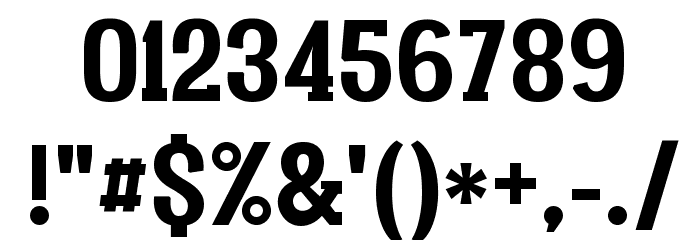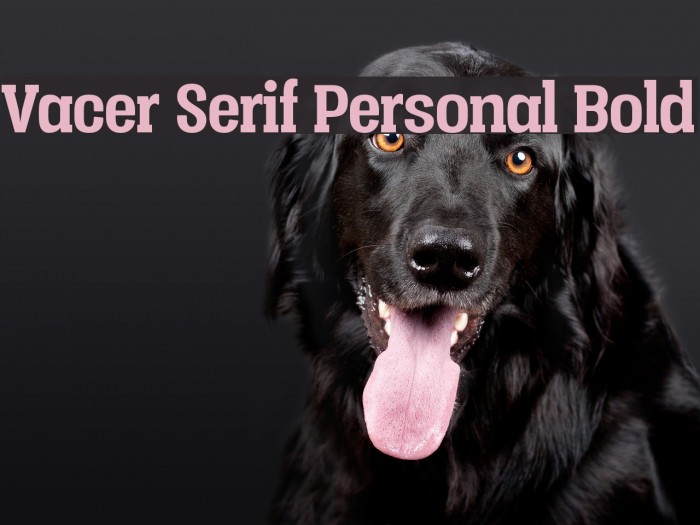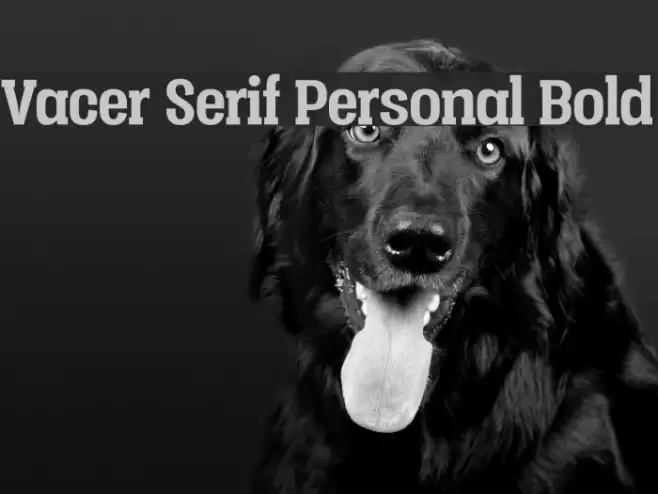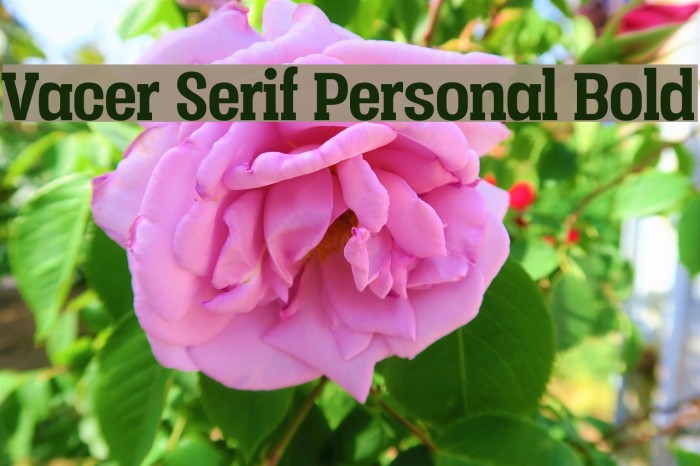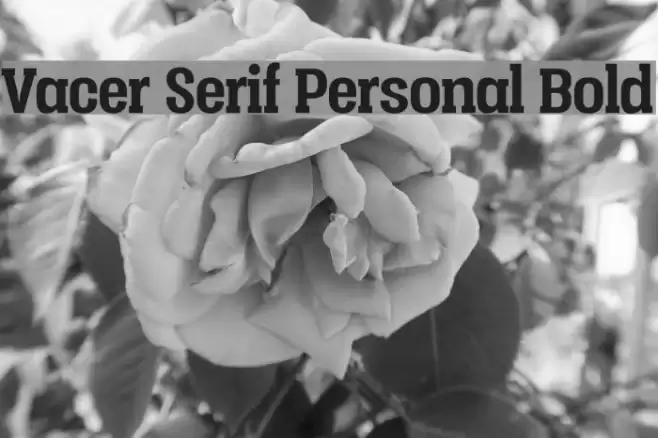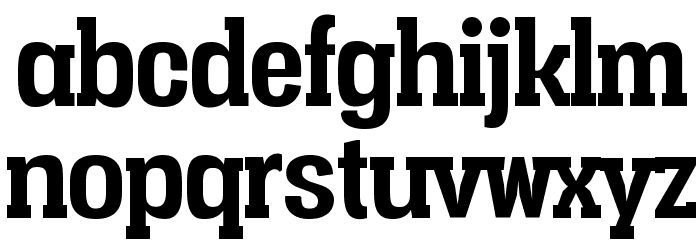
Vacer Serif Personal Bold Font
| Caz de utilizare | Headlines, Logos, Editorial Design |
| Proiecte propuse | Ideal for headlines, editorial design, branding, and signage where a classic and impactful look is desired. |